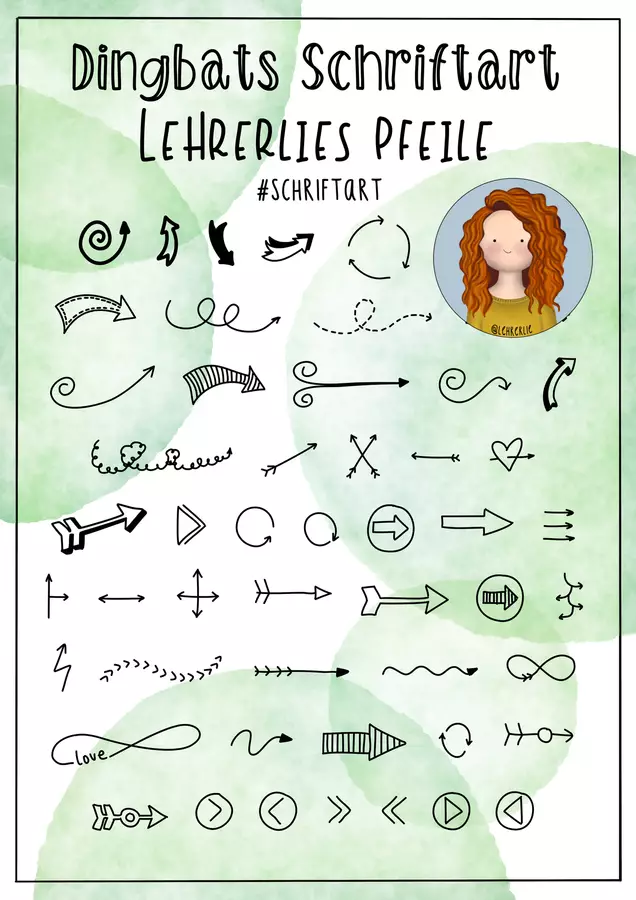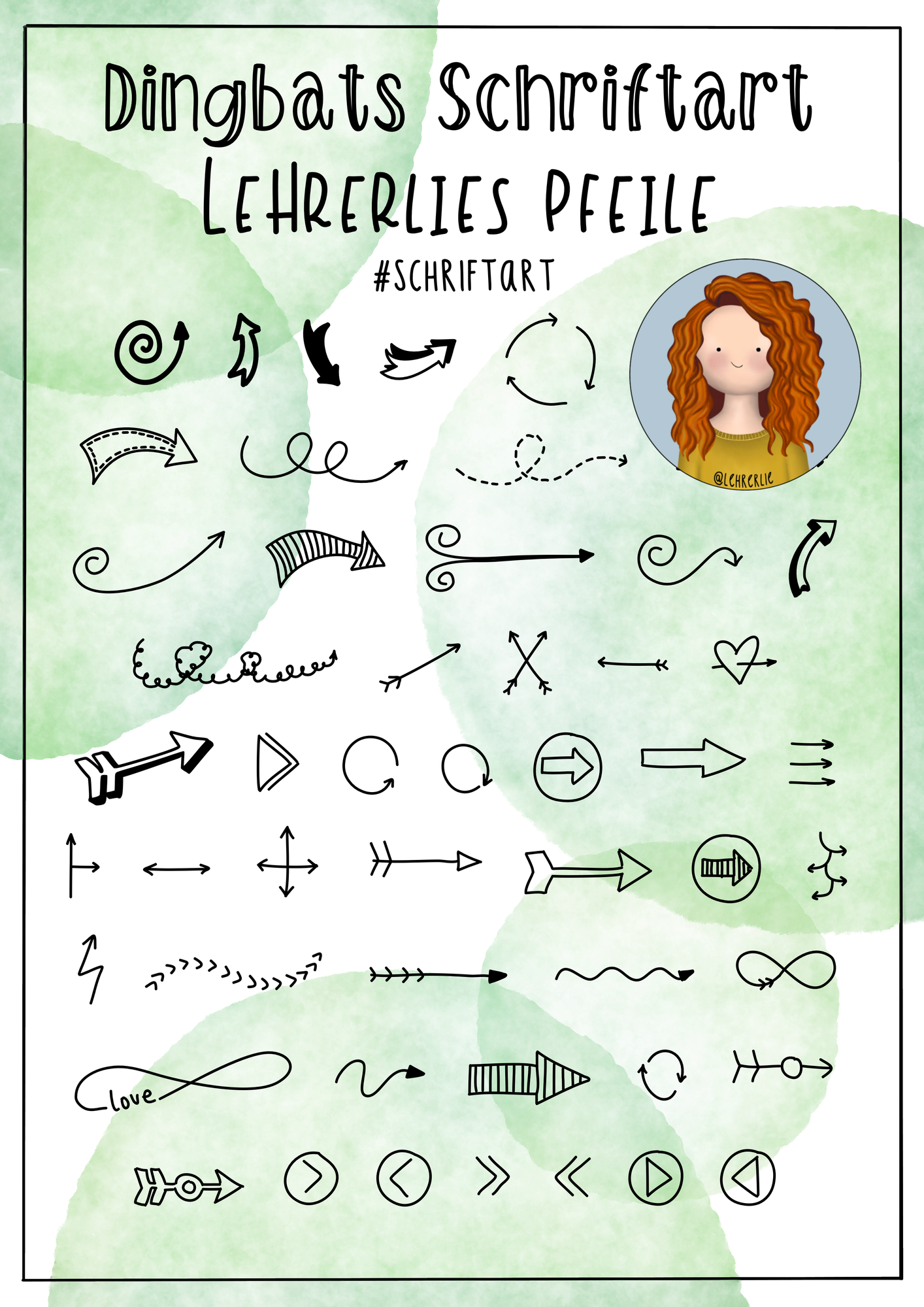
In diesem Material erhaltet ihr eine Dingbats-Schriftart. Sie besteht aus über 50 Pfeilen im Sketchnote-Style, mit welchen ihr eure Materialien in allen gängigen Programmen super einfach gestalten könnt. Einfach die Schriftart installieren und mit dem beiliegenden Fontposter das gewünschte Element auswählen.